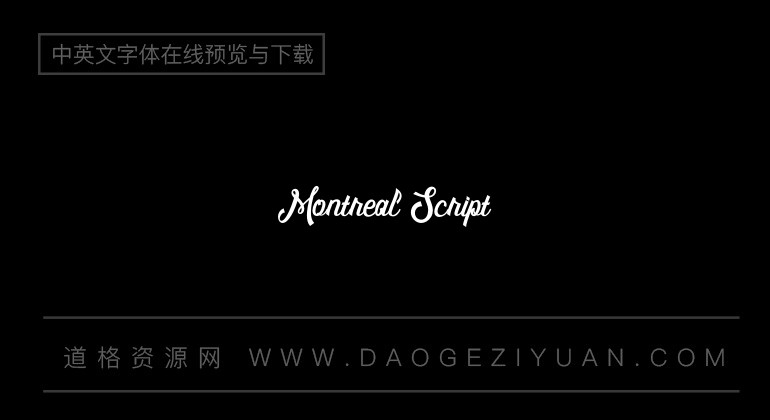
Montreal Script 是一种手写风格的字体,它具有流畅、自然的特点,常用于印刷品、广告和设计作品中。这种字体的特点是线条柔和、有弹性,形状比较优美,整体看起来非常舒适和优雅。 Montreal Script 字体具有多种字形和变化,包括粗体、斜体、加粗斜体等,可以根据需要进行选择。这种字体还包括多种特殊字符和符号,例如:大写和小写字母、数字、标点符号、箭头等等。 该字体由Sofia Mohr设计,适合用于设计漂亮的标题、标语、品牌名称、海报、明信片和其他创意设计项目。内容介绍
Montreal Script是一款非常不错的手写艺术字体,具有很好的视觉感,适合于文化类的宣传设计、商业类品牌的广告和产品包装设计以及个性化文字排版等较多场景。